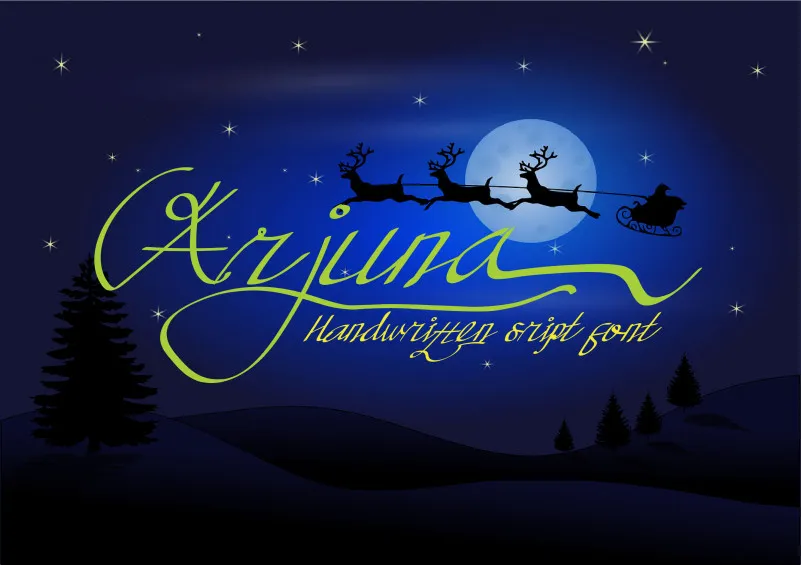
Arjuna Handwritten Font – Download Grátis
A ‘Arjuna Handwritten Font’ é uma peça que traz a autenticidade do papel de couro, com traços suaves e expressivos que parecem ter sido escritos com delicadeza por um verdadeiro artesão. Desenvolvida pelo designer chasim, essa fonte vem inspirada no estilo de escrever deslavado dos brasileiros daqui do nosso país, dando vida a palavras através de traços elegantes e leves que parecem flutuar no ar. Perfeita para personalizar sua marca ou projeto gráfico com uma sensação única e autêntica, essa fonte oferece um toque humano em qualquer design. Perdido nas nuances dos desenhos expressivos da ‘Arjuna Handwritten Font’, você terá a oportunidade de criar mensagens que se encaixam perfeitamente no estilo brasileiro, seja numa etiqueta de uma rede social ou num cartão de visita. Esta fonte é uma ótima maneira de incorporar um ar pessoal e autêntico ao seu trabalho gráfico, tornando cada projeto não apenas único, mas também muito mais emocionante para quem o vê.
Designer: chasim